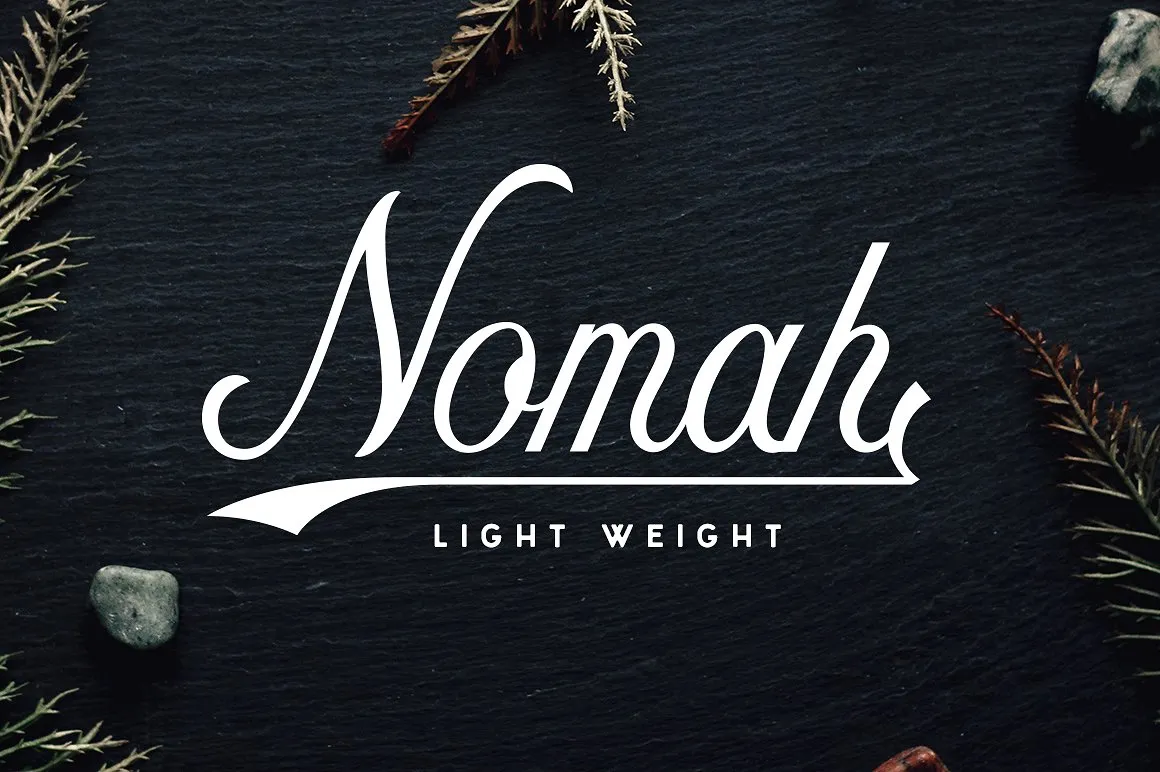
Nomah Light Script Font – Download Grátis
A fonte Nomah Light Script é uma opção perfeita para designers e criativos do Brasil, oferecendo um estilo elegante com uma personalidade forte. Desenhada pelo designer Nicolas Fredrickson, ela se destaca no mercado de fontes premium disponível na plataforma Creativemarket. Em seu design simplesmente encantador, a Nomah traz uma sensação vibrante e ativa que certamente será perfeita para dar vida aos seus logos, embalagens de produtos, camisetas personalizadas, convites e muito mais. A fonte tem um tom amigável e script elegante, com conectividade entre as letras do sinalizador a ponto d’água. Esta característica é rara em outros tipos de fones de texto, tornando-a única e valiosa para designers. A Nomah Light é apenas uma parte da fonte completa que também está disponível no seu estabelecimento virtual. Você pode visualizar vários pesos usando diferentes imagens acima. A fonte inclui caracteres europeus e se adapta perfeitamente para designers brasileiros, tanto na criação de materiais digitais quanto em impressões manuais. É uma opção excelente para aqueles que procuram um tipo de texto elegante e vibrante para seus projetos gráficos, seja ele digital ou físico. A fonte é livre para download e vem com todas as letras do alfabeto europeu, garantindo que você tenha a flexibilidade necessária para personalizar suas criações.